BRIO macht (Hoch-)Schule: Beim Münchner Typografie-Symposium"Umbruch"werden aus Holzschienen Buchstaben
Studenten der Design-Fakultät zeigen in einem Typografie-Workshop die Vielseitigkeit des BRIO-Klassikers
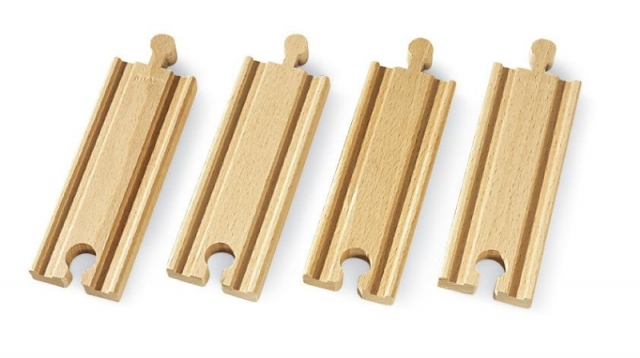
(firmenpresse) - Schwabach/München, 11. April 2011 - mein Teddy, mein Nutella, meine BRIO-Holzschienen - das sind die Begleiter fast jeder Kindheit. Auch viele Studenten der Fakultät für Design der Hochschule München haben diese Kindheitserinnerungen. Was liegt also näher, als die BRIO-Schienen wieder auszupacken, wenn man zum zweiten Mal in seinem Leben schreiben lernt? In einem Workshop im Rahmen des Münchner Typografie-Symposiums "Umbruch" beschäftigen sich Design-Studenten mit den Feinheiten der verschiedenen Schriftarten und formen dazu Buchstaben aus BRIO-Schienen.
BRIO erschließt für die Kleinen eine immer größere Welt an Schienenabenteuern mit Hafen, Frachtverkehr, Metro und vielen anderen Sets. Aber seit 1957 immer dabei ist die "gute alte" BRIO Holzschiene, gerade oder gebogen, als Weiche oder Brücke. Deshalb ist sie nicht nur perfekt zum darauf fahren, sondern auch zum damit schreiben.
Der Leiter des Workshops "BRIO Typeface" Christoph Walz dazu: "Die zahlreichen Module eignen sich über die Verwendung als Spielzeug hinaus ausgezeichnet, um innerhalb der geometrischen Grenzen differenzierte Buchstabenformen zu entwickeln. Die Erkundung des Gestaltungsystems und der unterschiedlichen Umsetzungsmöglichkeiten für ein und dasselbe Zeichen sowie deren Zusammenspiel als Font sind Gegenstand der Untersuchung." Die Studenten werden auf jeden Fall viel Spaß haben, vielleicht mit dem Nachbar zwei Kurven gegen eine Gerade tauschen und an manchen Buchstaben verzweifeln. Denn Seminarleiter Walz, der unter anderem die Infografiken für das ZDF Nachrichtenstudio entwarf, lässt sich kein X für ein U vormachen.